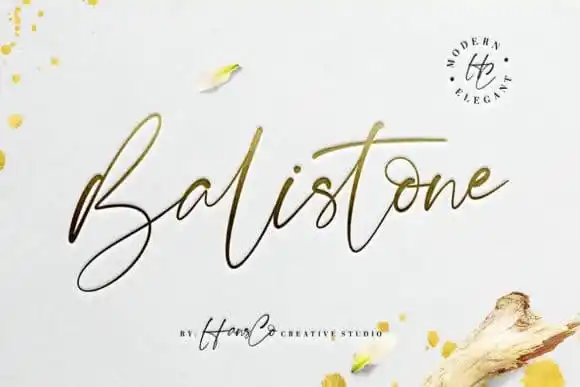
Balistone Handwritten Font – Download Grátis
A Balistone Handwritten Font é uma linda e elegante tipografia escrita a mão, ideal para criar designs únicos e modernos. Este tipo de letra traz consigo características como um baseline variável, linhas macias, belos grafitos e alternativas maravilhosas que garantem personalidade e originalidade. HansCo criou esta fonte especialmente para inspirar você a criar designs inovadores e estilosos. O PUA Encoding permitirá que você acesso facilmente todos os gráficos e salsichões, tornando essa fonte uma opção perfeita para projetistas de tudo o que buscam em uma tipografia escrita a mão. Fique encantado com sua beleza única e leve e use-a para trazer vida ao seu design.